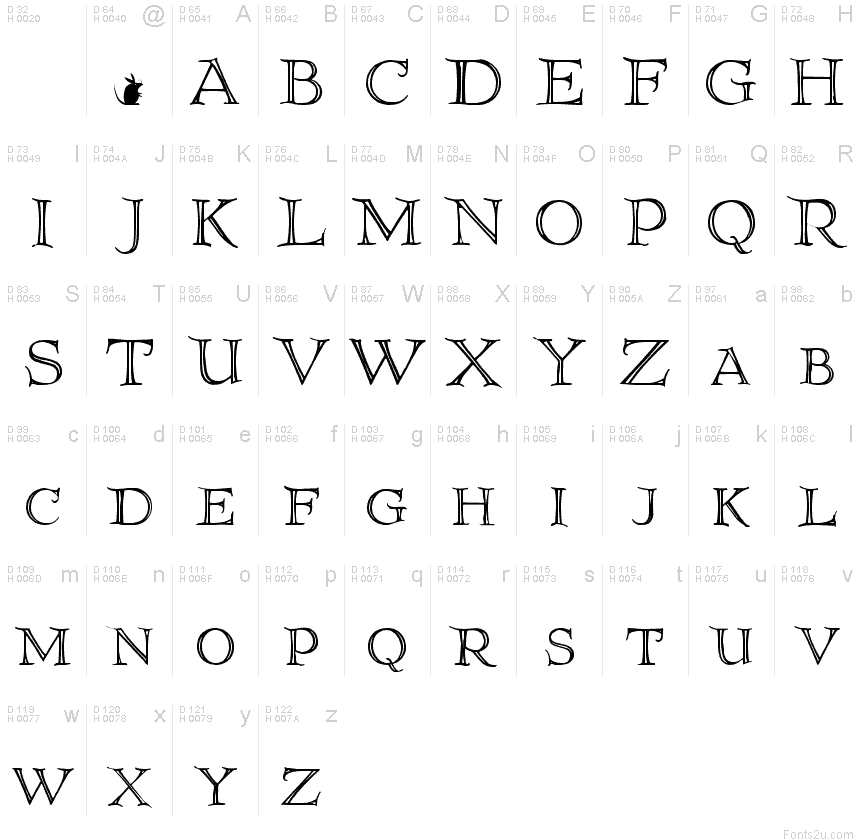
Elliottland J، خط عرض (display) جذاب من تصميم Julius B. Thyssen، يفيض بلمسة ريترو مبهجة. أشكاله الجريئة والمعبرة وزواياه المعقدة تستحضر عبق الماضي، مما يضفي شعوراً بالحنين وسحراً خالداً. وبفضل طابعه الفريد، يتناسب هذا الخط بشكل رائع مع مجموعة واسعة من التصاميم، بدءاً من العلامات التجارية المستوحاة من الطراز القديم وتنسيقات المطبوعات، وصولاً إلى العناوين اللافتة والملصقات المؤثرة.
تجمع جماليات Elliottland J الفريدة بين الماضي والحاضر بسلاسة، مما يجعله خياراً متعدد الاستخدامات لأولئك الذين يسعون لإضفاء لمسة من الجاذبية الكلاسيكية على إبداعاتهم.